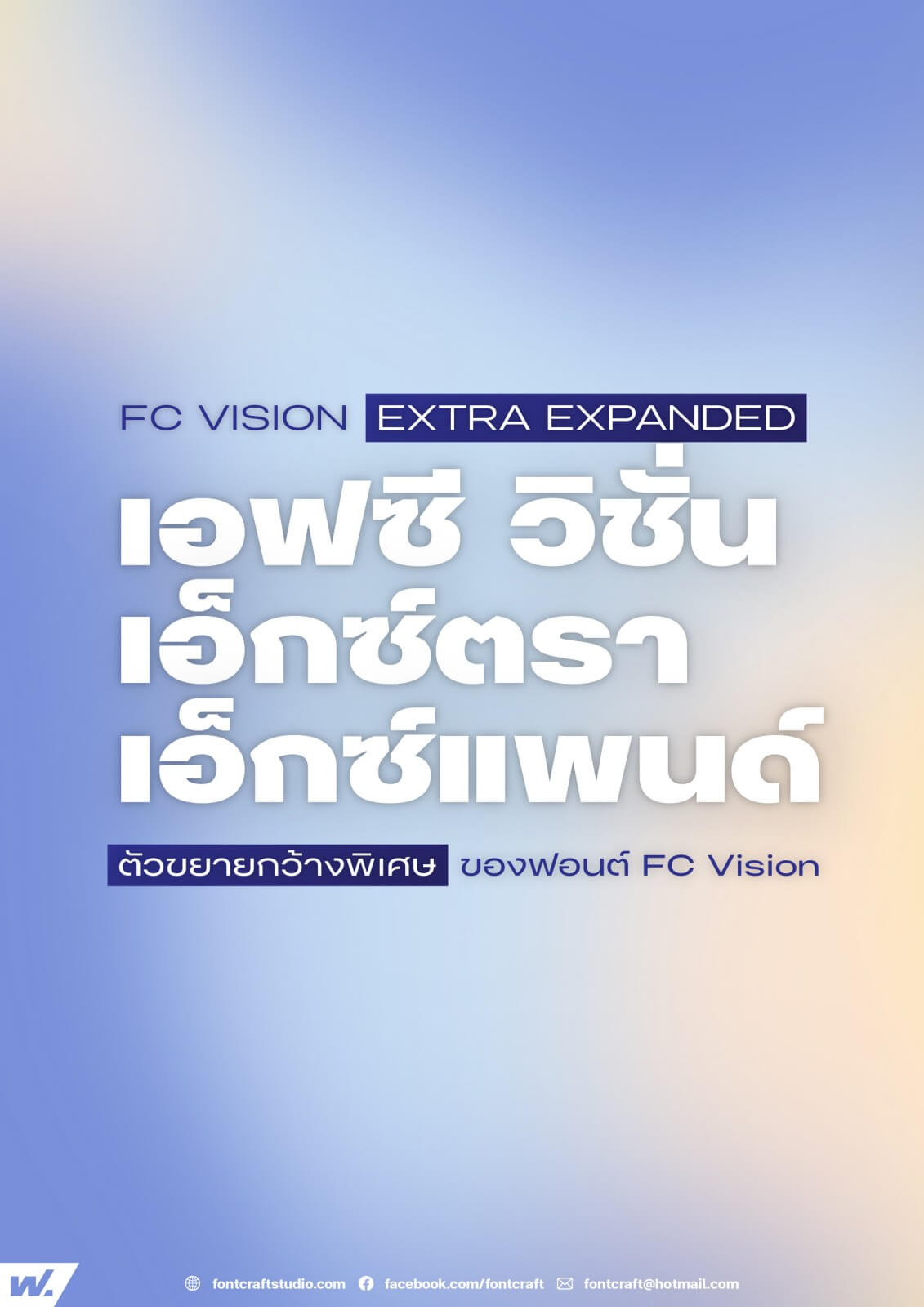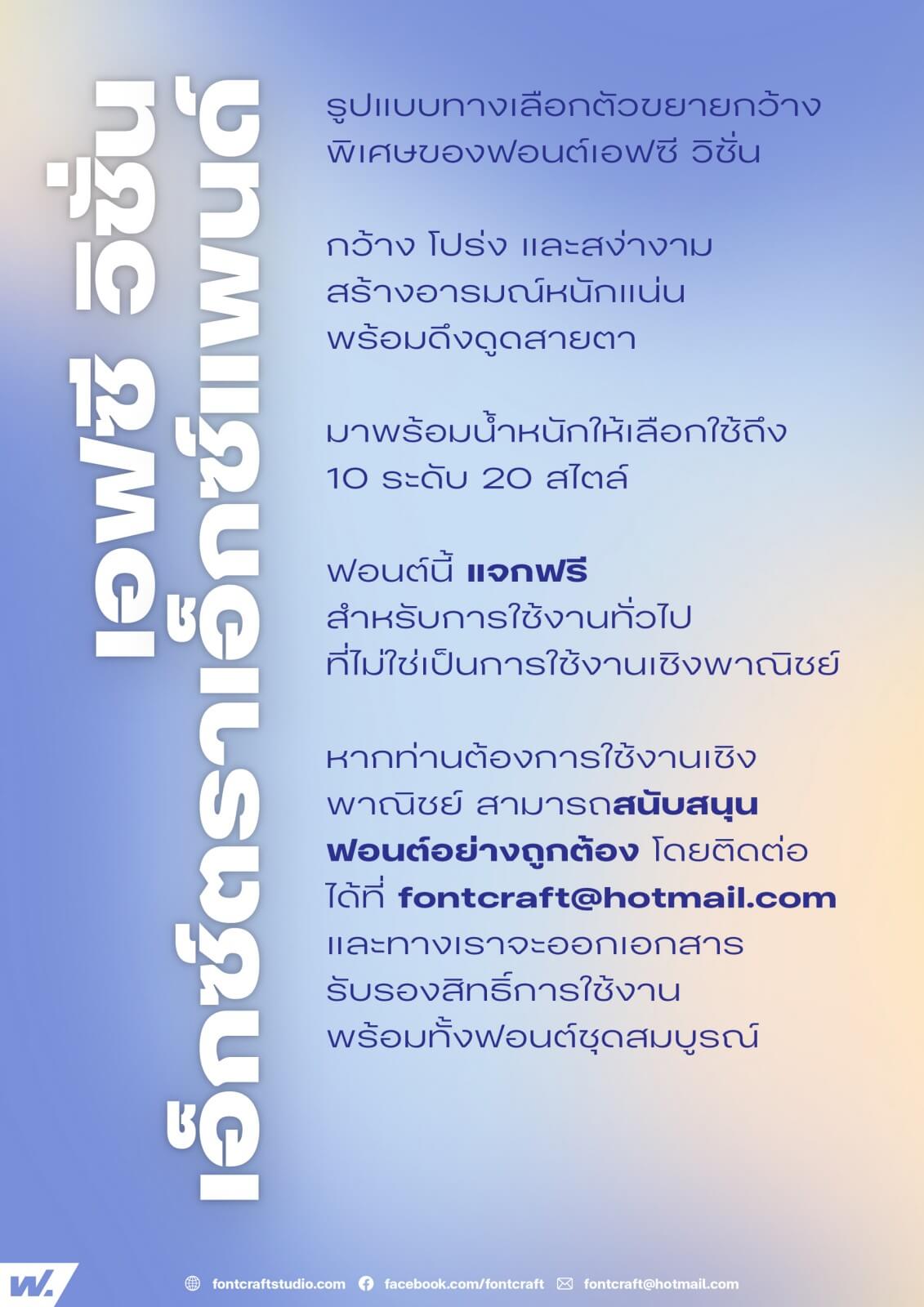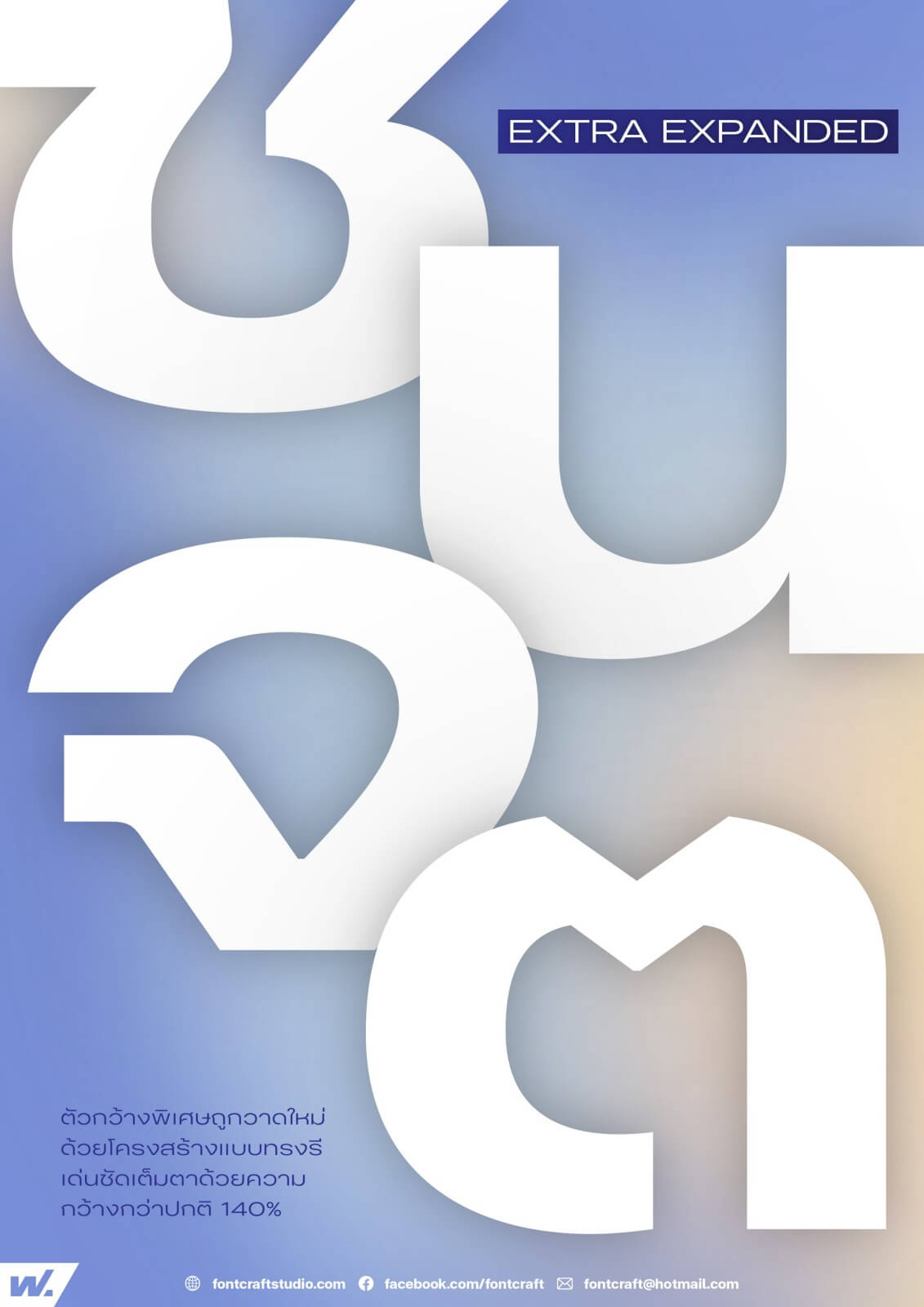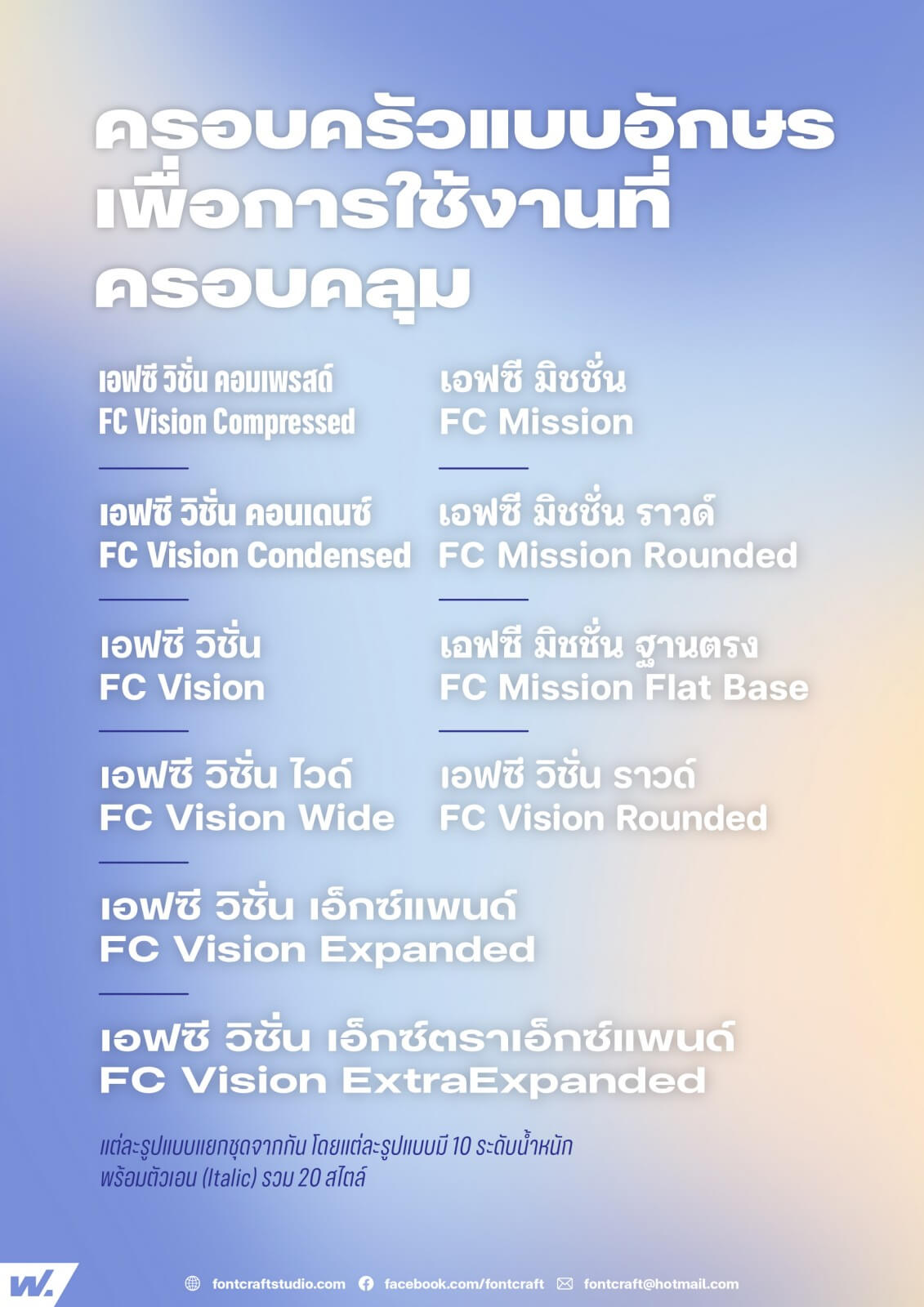
รูปแบบทางเลือกตัวขยายกว้างพิเศษ กว้างที่สุดในของ FC Vision Superfamily กว้าง โปร่ง และสง่างาม สร้างอารมณ์หนักแน่น พร้อมดึงดูดสายตา
ข้อมูลคอมพิวเตอร์ฟอนต์: เอฟซี วิชั่น เอ็กซ์ตราเอ็กแพนด์ (FC Vision ExtraExpanded)